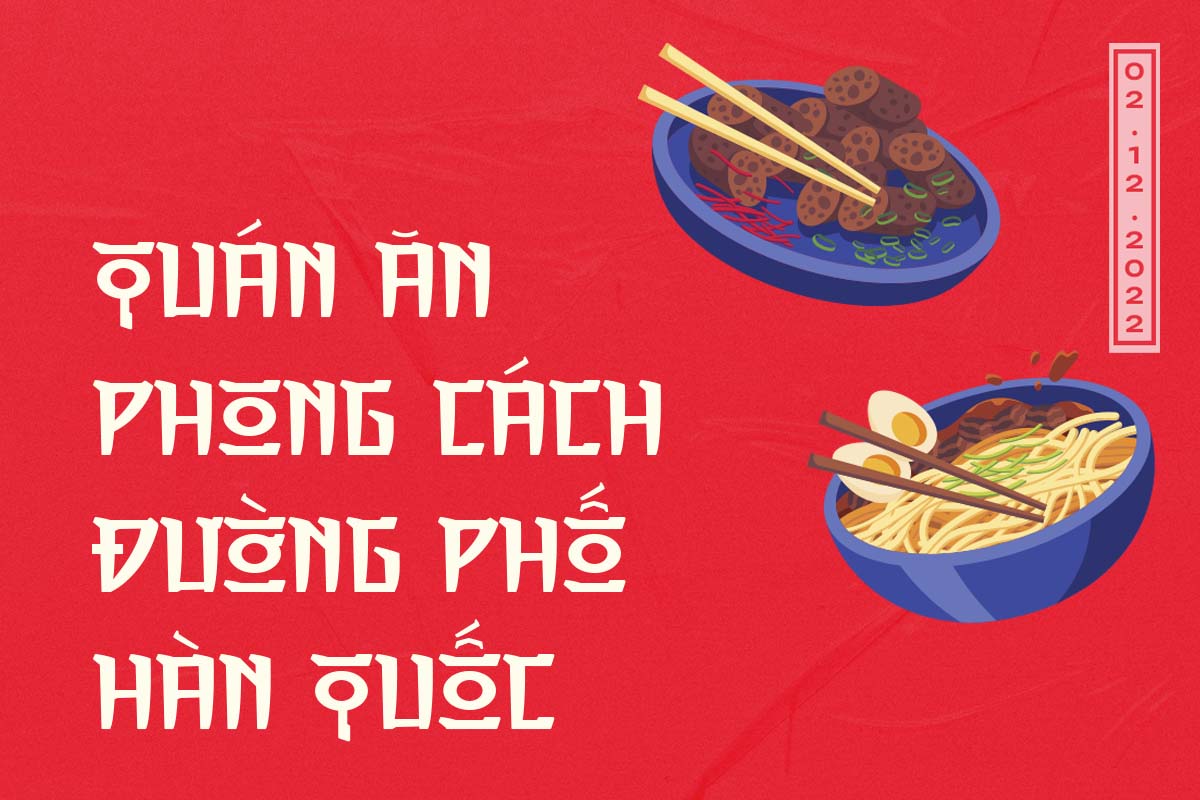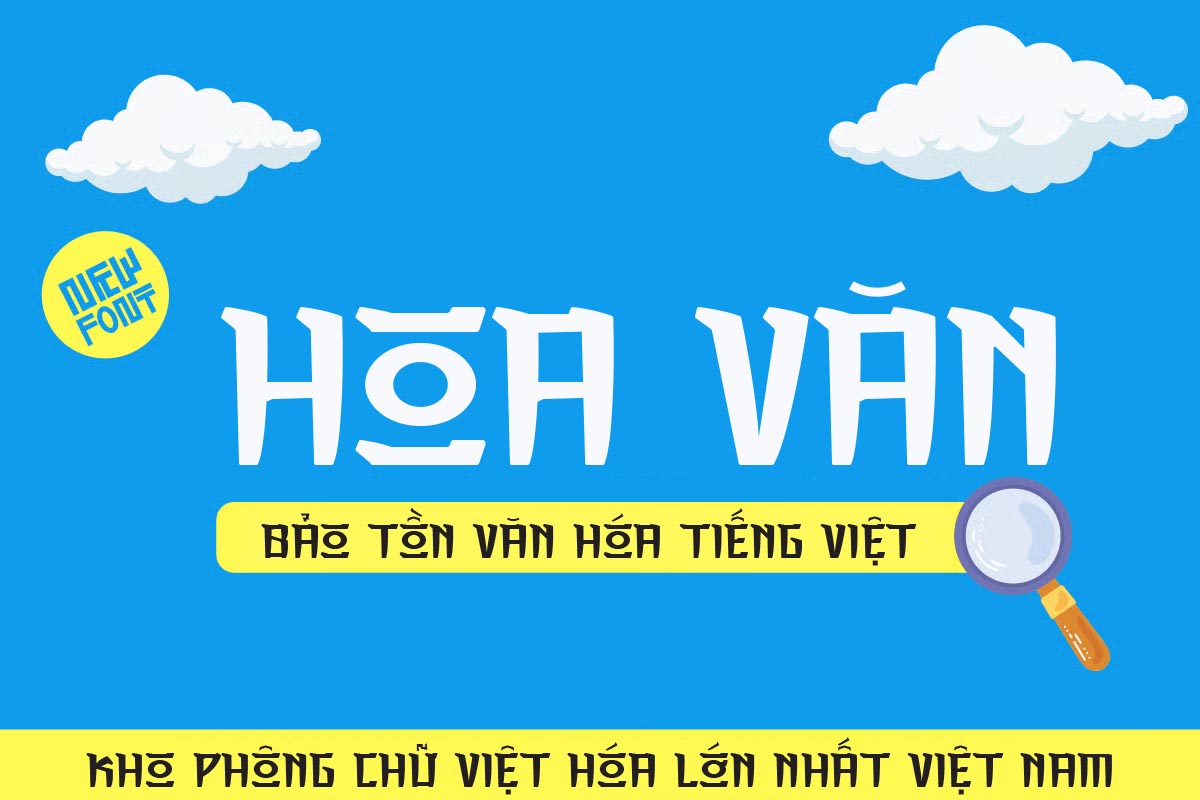
Font chữ Hàn Quốc Việt Hóa TH Joypor Phong Cách Chữ Hangeul
Nếu bạn đang tìm kiếm một làn gió mới mang đậm âm hưởng Á Đông cho các dự án thiết kế của mình, TH Joypor chính là sự lựa chọn hoàn hảo. Được phát triển từ nguyên bản Joypor do IHDSTD Studio sáng tạo, đây là một mẫu font chữ hàn quốc vô cùng độc đáo, mô phỏng lại những đường nét đặc trưng của bảng chữ cái Hangeul nhưng lại được thể hiện mượt mà qua các ký tự Latinh quen thuộc.
Font chữ Hàn Quốc Việt Hóa TH Joypor
Đặc Điểm Nổi Bật Của Phông Chữ
Sức hút của Joypor nằm ở sự kết hợp khéo léo giữa cấu trúc hình học vuông vức và các đường bo góc tinh tế. Phông chữ này mang đến một diện mạo vừa hiện đại, năng động lại vừa giữ được nét văn hóa truyền thống.
Là một Display Font (phông chữ hiển thị) xuất sắc, TH Joypor sinh ra để làm tâm điểm cho mọi ánh nhìn. Phông chữ cực kỳ phù hợp để ứng dụng trong các thiết kế poster, bao bì sản phẩm, logo thương hiệu, menu nhà hàng hay các chiến dịch truyền thông mang hơi hướng K-pop và văn hóa giới trẻ.
Tại Sao Nên Sử Dụng Phiên Bản Việt Hóa TH Joypor?
Trong thiết kế đồ họa, việc sử dụng các phông chữ nước ngoài thường gặp rào cản lớn về dấu câu, dẫn đến lỗi hiển thị hoặc phá vỡ cấu trúc thẩm mỹ nguyên bản. Tuy nhiên, với phiên bản font chữ Việt hóa mang tên TH Joypor, rào cản này đã được xóa bỏ hoàn toàn.
Dự án này được thực hiện bởi TH Team – một đội ngũ đầy nhiệt huyết và có chuyên môn cao trong việc bản địa hóa typography tại Việt Nam. TH Team đã dành nhiều tâm huyết để nghiên cứu, thêm thắt và căn chỉnh từng dấu câu tiếng Việt (sắc, huyền, hỏi, ngã, nặng) sao cho đồng nhất tuyệt đối với độ dày và nhịp điệu nét chữ của IHDSTD Studio. Nhờ đó, các designer có thể thoải mái sáng tạo nội dung tiếng Việt mà vẫn giữ nguyên được tinh thần nguyên bản của một font chữ hàn quốc thực thụ.
TH Joypor không chỉ là một công cụ thiết kế đơn thuần, mà còn là chiếc cầu nối văn hóa thú vị giúp các tác phẩm đồ họa của bạn trở nên phá cách và thu hút hơn. Hãy bổ sung ngay font chữ Việt hóa chất lượng này vào bộ sưu tập typography của bạn để sẵn sàng cho những dự án bùng nổ sắp tới.